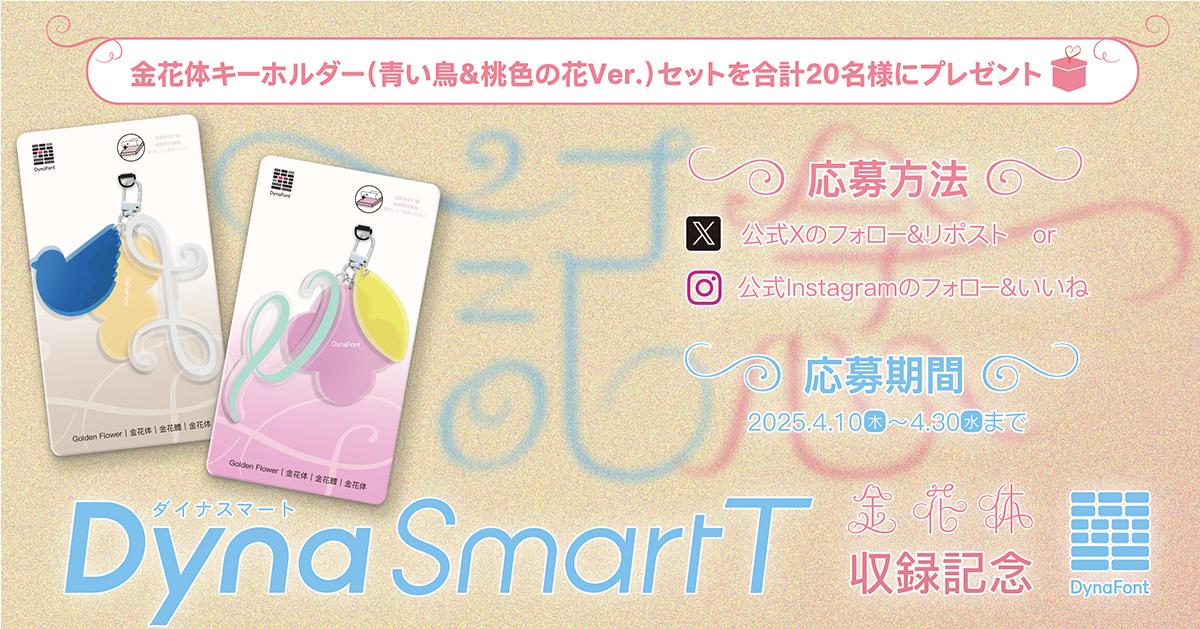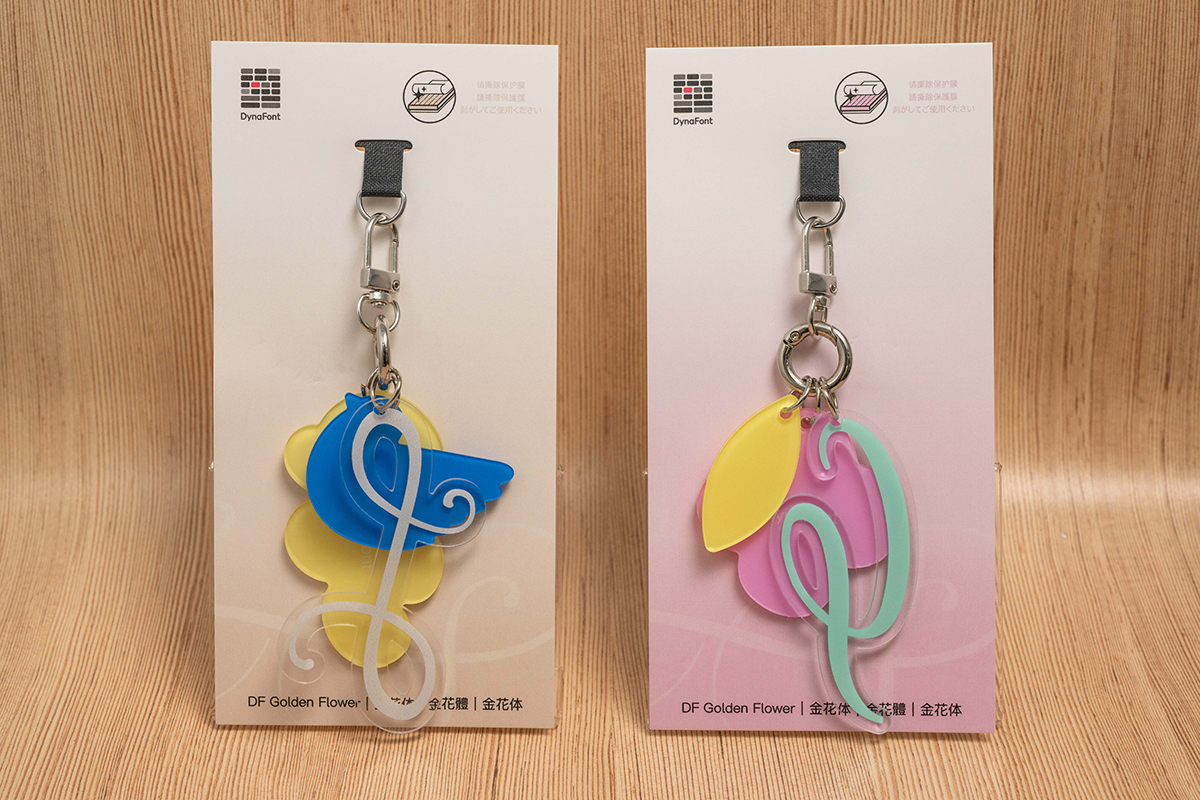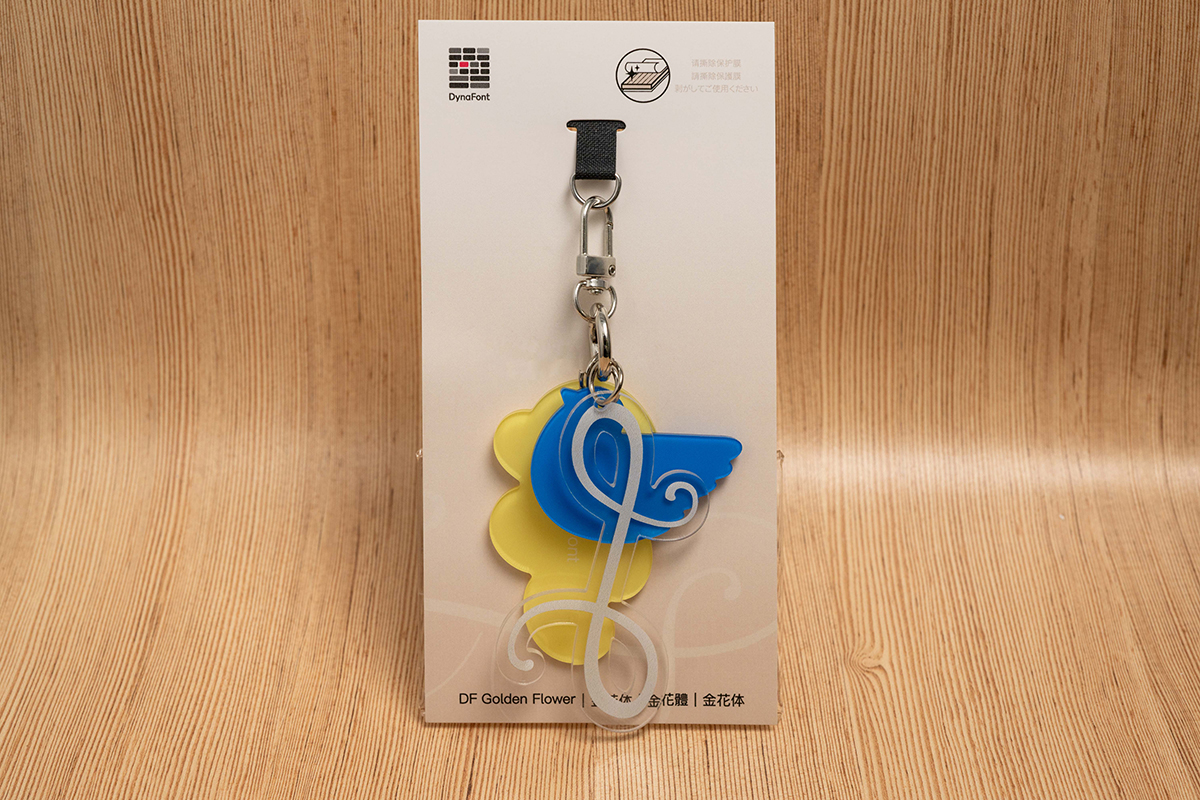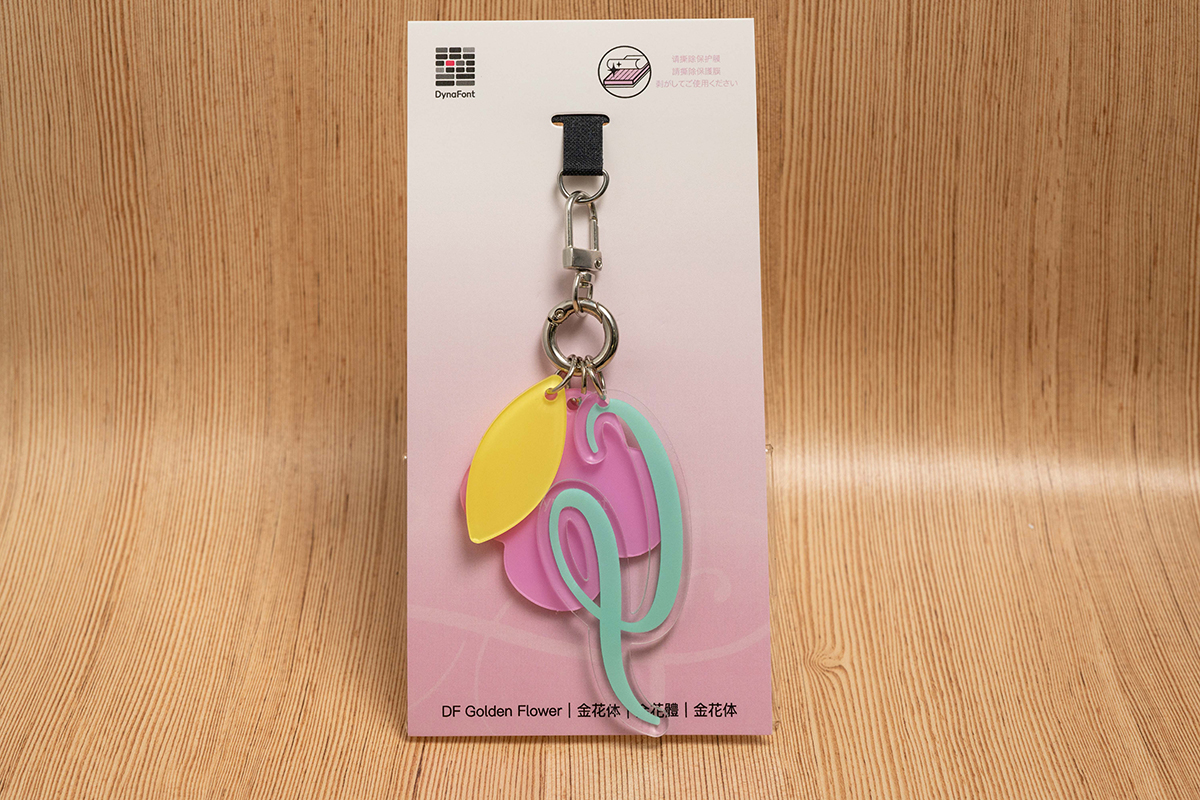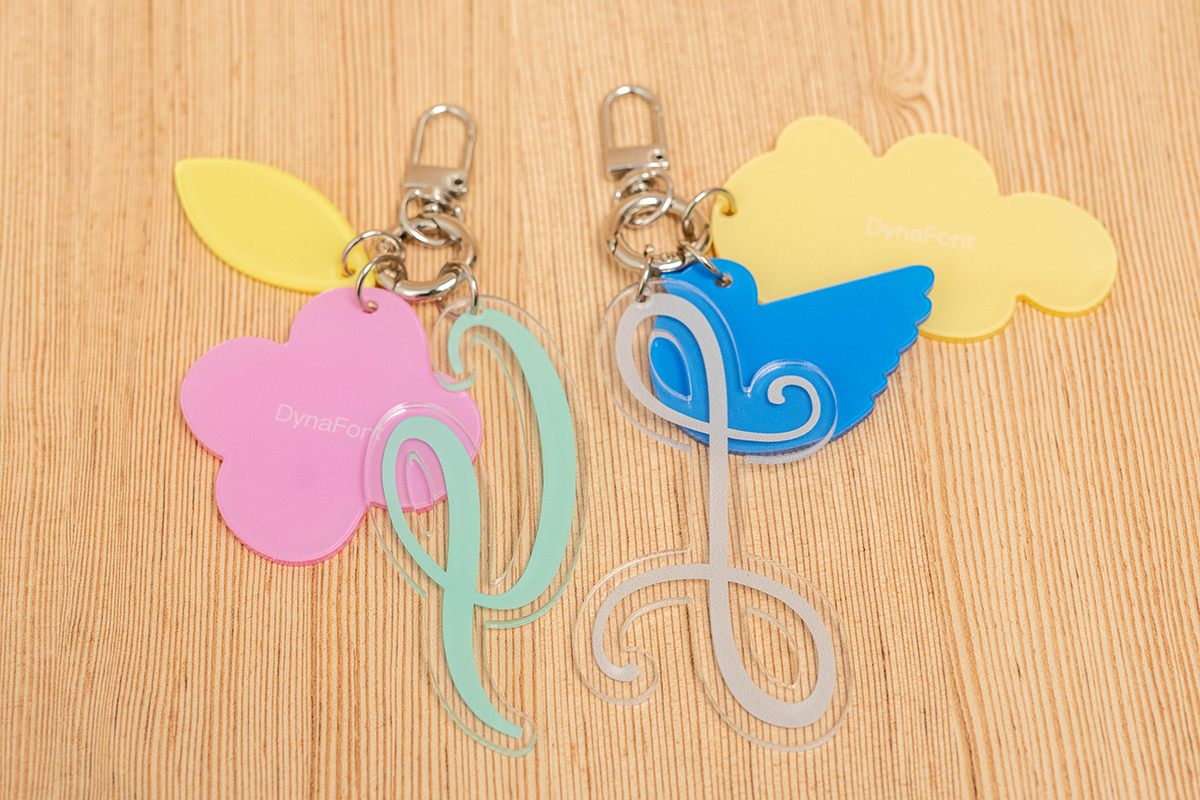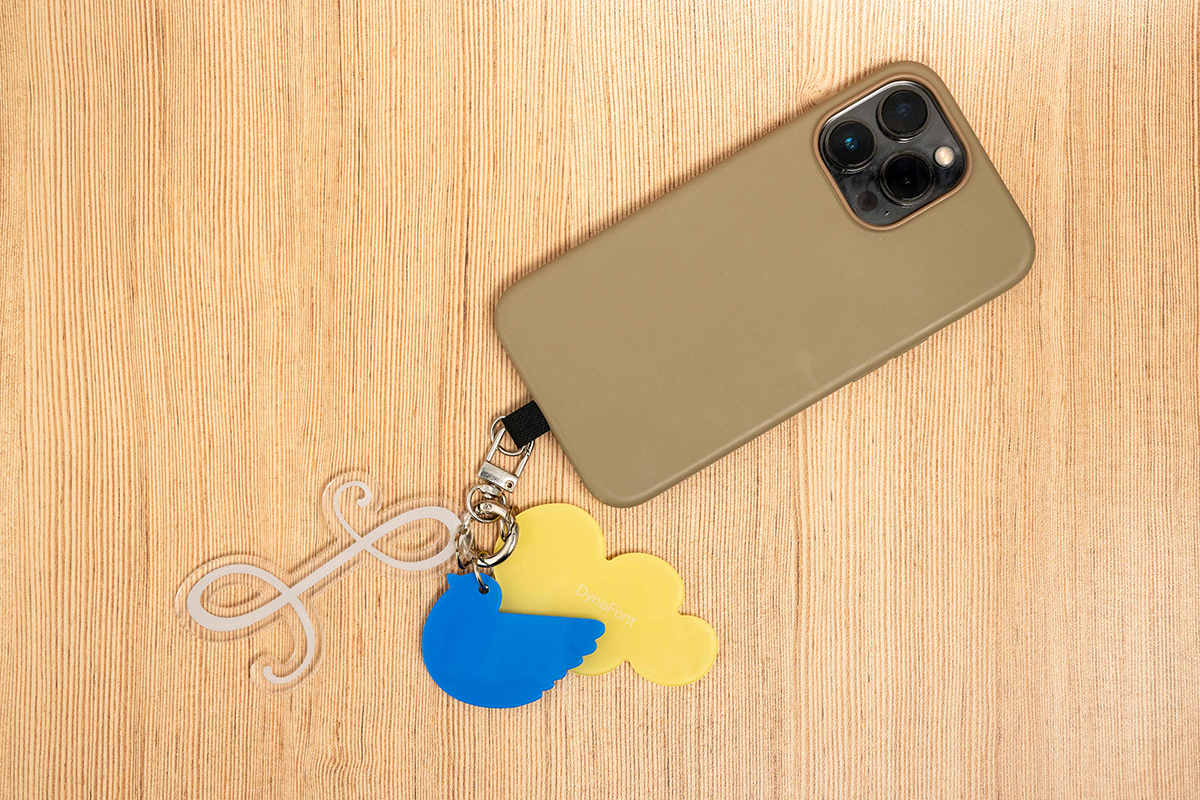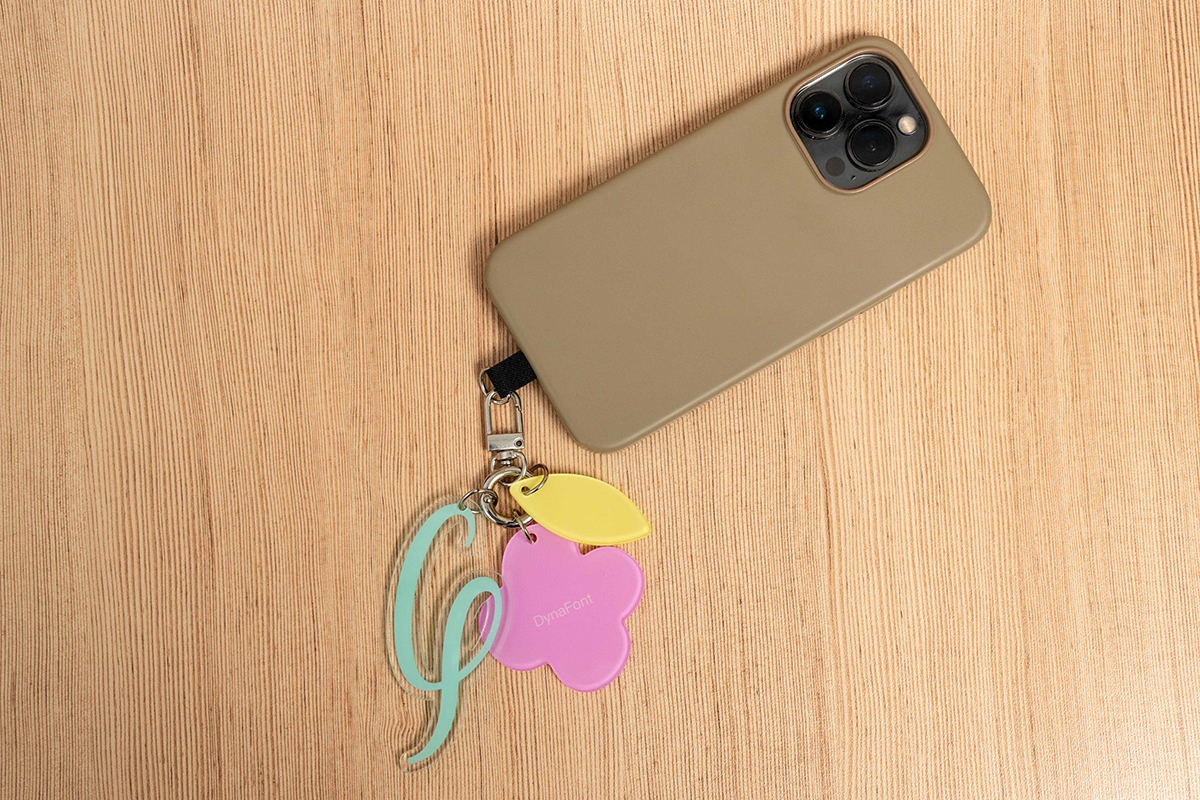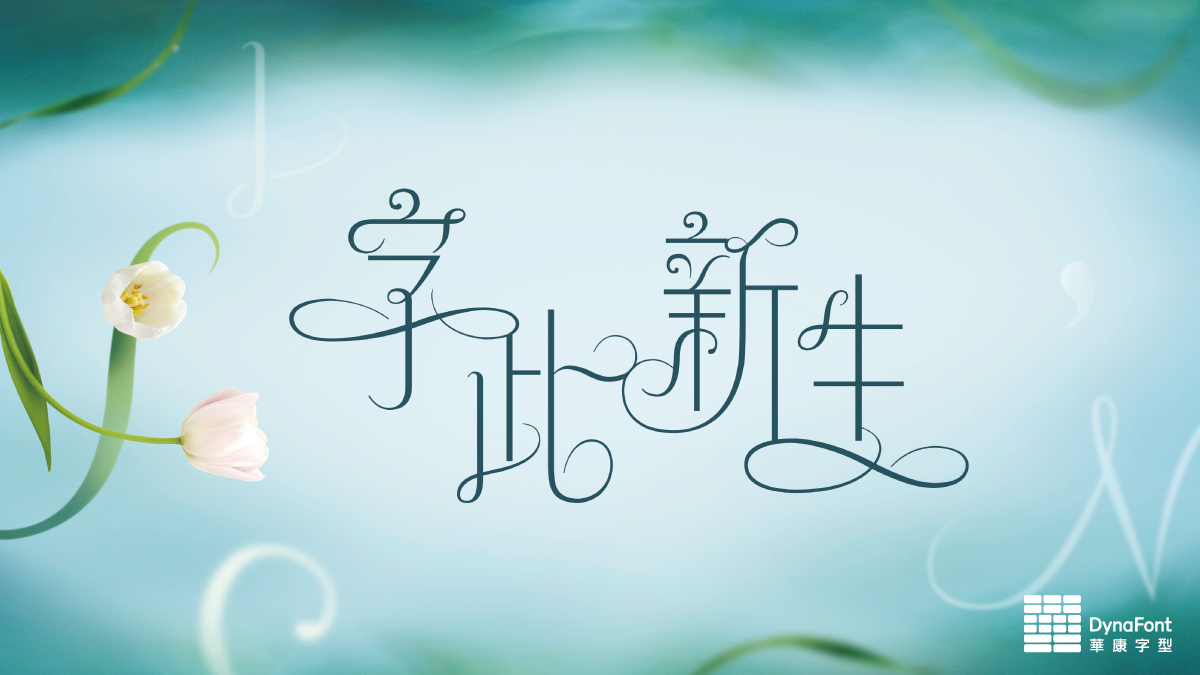
特別な瞬間を祝福するダイナフォント「金花体」の「DynaSmart T」収録記念キャンペーンを4月30日迄開催。抽選で20名に「ダイナフォント金花体キーホルダーセット」をプレゼント
日常を美しく特別な時間に変える「ダイナフォント金花体キーホルダー」
「ダイナフォント金花体キーホルダー」は、2024年7月に中国・上海で開催したダイナコムウェア「文字より新生へ」芸術展のオリジナルグッズとして制作、「文字より新生へキーホルダー」をリデザインした2種類のキーホルダー。ダイナコムウェアを代表する書体デザイナーであるOliveがデザインした特別な瞬間を祝福する文字「金花体」のビジュアルを採用しており、アクリルの保護フィルムを剥がすことで光沢が出て「金花体」の華やかさをより味わうことができる。
特別な瞬間に美しく咲く感情の文字「金花体」がDynaSmart Tに収録開始
「金花体」は、「金文体」をはじめ、グッドデザイン賞を受賞した「金蝶体」や「甲金文体」などダイナフォントを代表する数々の書体を手掛けてきたダイナコムウェア株式会社の書体デザイナー・Oliveによるロマン風書体。感情を伝える際に使用されてきた西洋のカリグラフィーと東洋の漢字の金文といった東西の文化を融合させ、生命力に溢れ流れるような曲線美が特別な瞬間に湧き上がる感情を美しく咲く花のように表現する。
ダイナコムウェア「文字より新生へ」芸術展
ダイナコムウェア「文字より新生へ」芸術展は、これまでの文字に関する固定観念を覆した書体デザインが持つ無限の可能性とその独特の生命力を展示することを目的に2024年7月24日から28日までの期間、中国・上海にて開催した芸術展。期間中、多くの来場者がダイナフォントを通じて文字文化に触れ、書体デザインに強い興味に持った。